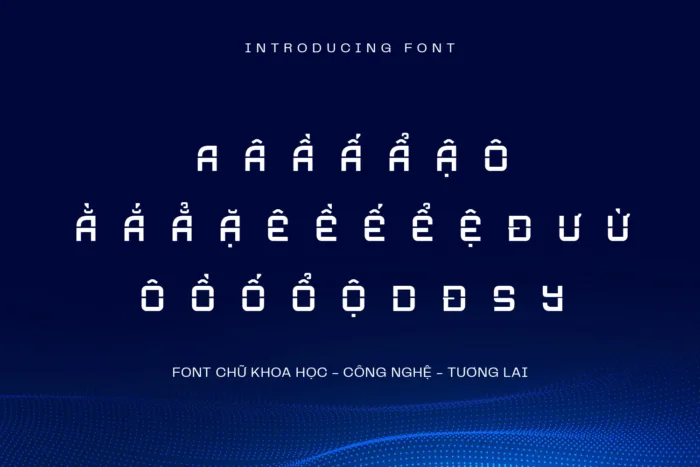
DVN Hexabot – Font chữ Việt hóa đậm chất tương lai và công nghệ
DVN Hexabot là một kiểu chữ hiện đại mang cảm hứng từ thế giới công nghệ, robot và tương lai. Với cấu trúc hình học mạnh mẽ, các nét cắt vuông vức và kiểu dáng mô-đun độc đáo, font chữ này gợi nhớ đến giao diện của các hệ điều hành trong phim khoa học viễn tưởng hay bảng điều khiển của robot AI. DVN Hexabot được Việt hóa trọn bộ, hỗ trợ đầy đủ dấu tiếng Việt, giúp bạn dễ dàng ứng dụng trong các dự án sáng tạo như thiết kế poster, tiêu đề game, giao diện UI, branding công nghệ, hay bìa tạp chí kỹ thuật số. Font mang đến cảm giác mạnh mẽ, hiện đại và nổi bật, phù hợp với các thiết kế mang hơi thở cyberpunk, digital hoặc industrial. Nếu bạn đang tìm kiếm một phông chữ độc đáo, đầy cá tính và mang dấu ấn tương lai, DVN Hexabot chính là lựa chọn không thể bỏ qua.
Ứng dụng gợi ý:
• Poster phim khoa học viễn tưởng (sci-fi, cyberpunk)
• Giao diện UI/UX cho app công nghệ, AI, IoT
• Tiêu đề game thể loại futuristic, mecha, robot
• Logo startup công nghệ, phần mềm
• Bìa tạp chí số, blockchain, AR/VR
• Sản phẩm NFT, digital art
• Banner các sự kiện hackathon, tech meetup